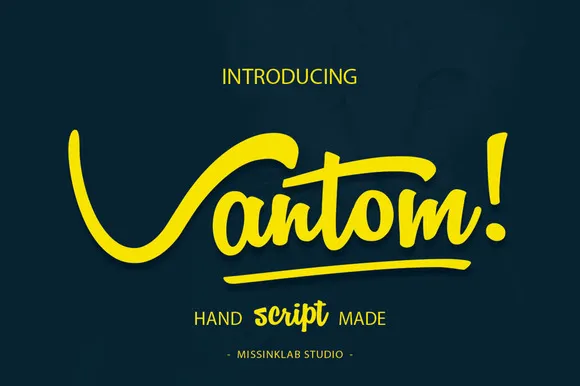
Vantom Script Font – Download Grátis
Vantom Script Font é uma opção única para quem busca uma tipografia com estilo moderno que também transmite sentimentos suaves e emocionantes. Esta fonte script vem diretamente do coração dos designer 178-MC, criando um ambiente onde a fidelidade ao original é preservada enquanto o resultado final é tão fluido quanto uma escrita manuscrita real. O design de Vantom Script Font traz à tona os detalhes delicados e as nuances suaves do estilo script, proporcionando uma experiência visual atraente. O resultado é uma fonte que não apenas desempenha bem em qualquer documento ou projeto gráfico, mas também se torna um elemento emocional ao incorporar emoções e sentimentos na forma como os textos são apresentados. Com sua designação de 178-MC, Vantom Script Font oferece aos designers a chance de expressar suas próprias visões em letras elegantes, fluidas e profundamente personalizáveis. Através deste recurso visual, o designer pode criar uma experiência única que fale diretamente ao coração do seu público-alvo.